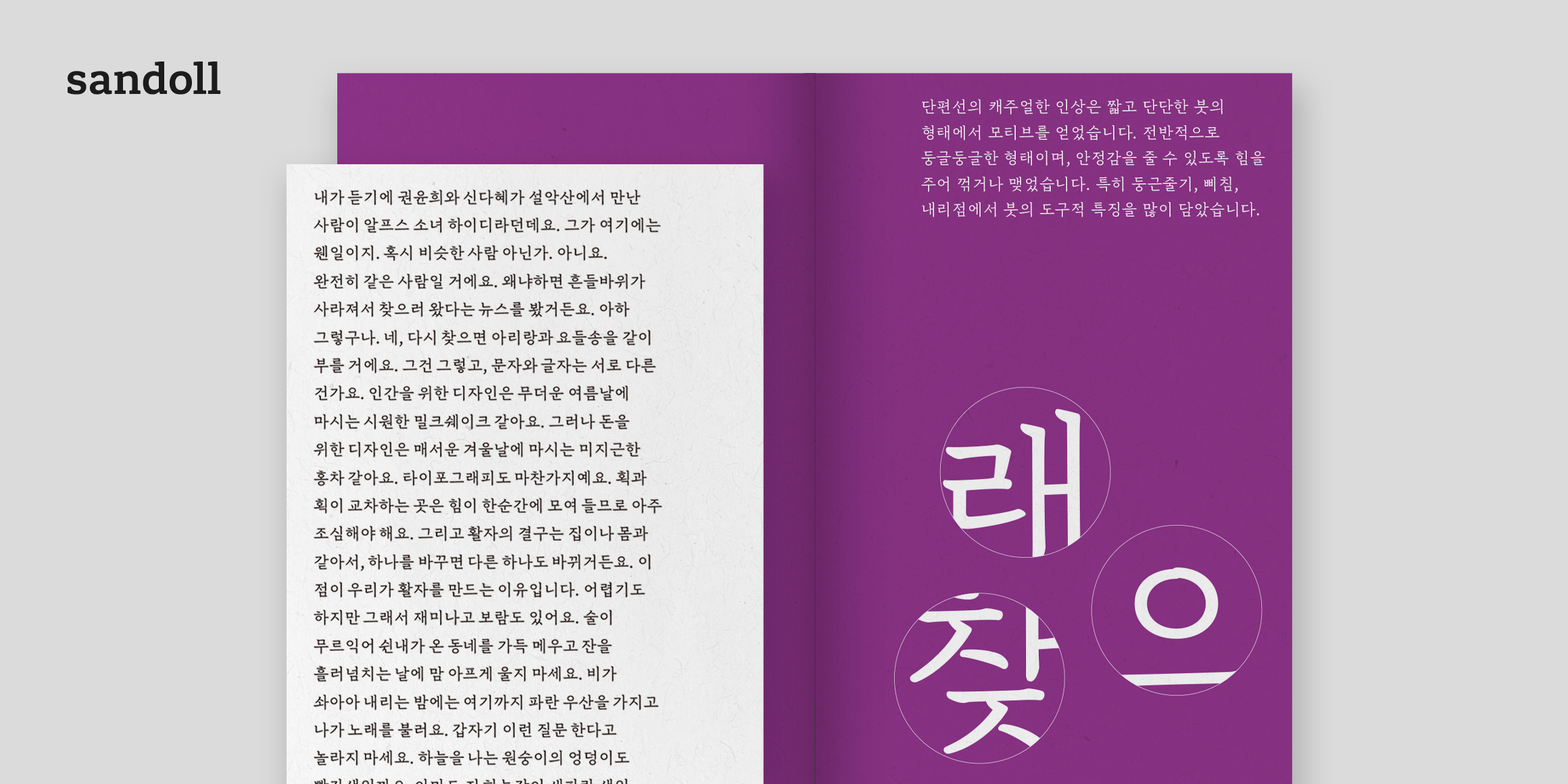
Sandoll 단편선 바탕
산돌 단편선은 부족한 본문 활자군의 선택지를 넓히기 위해 기획된 캐주얼한 인상의 활자 가족입니다.
큼지막하게 그려진 획들이 시원한 느낌을 주며, 글자의 속공간이나 사이공간도 크게 나뉘었기 때문에 조판시 단정하고 넉넉한 분위기를 줄 수 있습니다. 또한 각 패밀리마다 서체의 인상과 분위기가 동일하게 유지되기 때문에 바탕과 돋움, 가로짜기와 세로짜기를 혼용해도 이질감 없는 조판이 가능합니다.
웨이트에 따라 본문과 제목에 모두 사용할 수 있으며 비문학보다는 문학에, 장편보다는 단편에, 전통적인 글보다는 현대적인 글에 사용하기 좋습니다.
*단편선 바탕의 01, 02 웨이트는 가로쓰기 전용, 03, 04 웨이트는 세로쓰기 전용으로 제작되었습니다. 세로쓰기 전용 글자와 문장 부호의 형태가 상이하니 구매 시 유의 바랍니다.